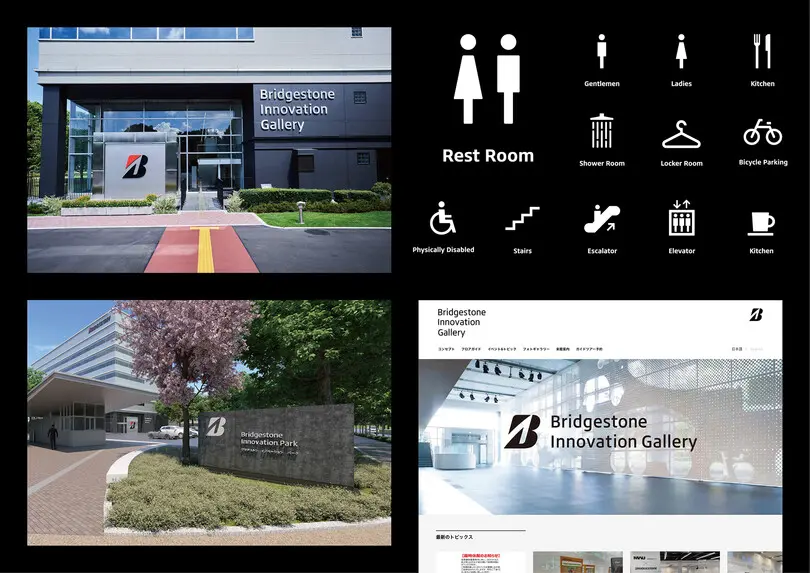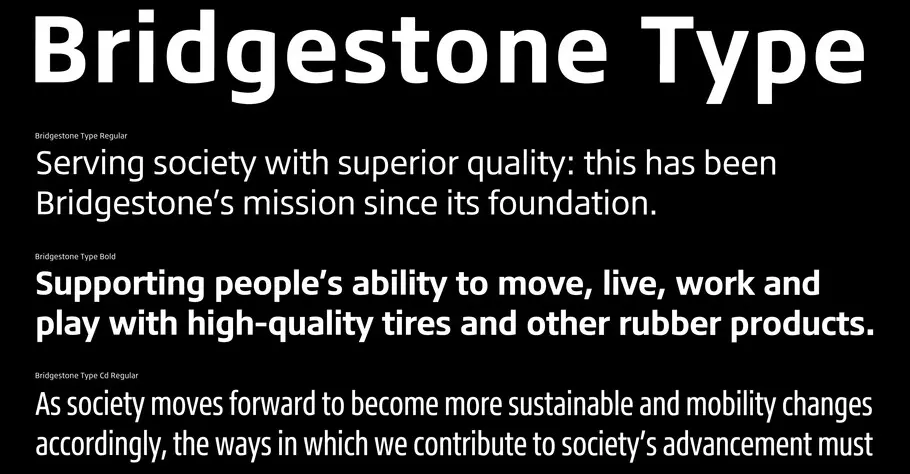
ブランドアイデンティティを反映したブリヂストンの欧文コーポレートフォント
2020年、ブリヂストンは新たなブランドアイデンティティを導入するにあたり、「ブリヂストンらしさ」を表現するツールとして欧文コーポレートフォントの開発を決定。
ブリヂストンでは、「社会の進歩に貢献する」というブランドパーパスを実現するためのアプローチとして3つのC(Care:安心、Confidence:信頼、Creativity:創造力)が定義されています。この考え方をコーポレートフォントとして体現し、グローバルでのブランド表現統一を実現するために、ブリヂストンのデザイン部門、Monotypeの小林章と土井遼太がディスカッションしながら試作を重ねました。
ブリヂストン流の「デザインコード」や評価・検証プロセスを活用することでブランドアイデンティティの概念をデザインとして取り入れる一方、ブリヂストンのロゴタイプとのマッチングを考慮して文字のバランスやイタリック体の角度を調節するなど、細部の仕様にも徹底的にもこだわっています。
また、国内だけでなく、海外の担当者の意見も取り入れながら検討し、制作を進めることで、「みんなで作り上げた自分たちのためのフォント」という意識が生まれ、ブランドに対する意識向上、一体感、プライドの醸成といったインターナル・ブランディング面での効果も得られました。
完成したオリジナルの欧文コーポレートフォント Bridgestone Typeのファミリーは、Regular、Medium、Boldとそれぞれのイタリック体、コンデンス体を合わせた計12ウェイト。高い可読性、視覚的な安定感、多様なメディアでの明瞭性、コンパクトな字幅によるスペースの節約、シンプルなエレメントによる機能美を備えており、ブリヂストンらしいブランド表現の核として様々なグラフィックデザイン、ロゴや対外発表などあらゆるタッチポイントで積極的に活用されています。
Bridgestone Type は、2021年度グッドデザイン賞を受賞。創立から90年を迎える同社のブランドデザインにおいても大きな成果となりました。